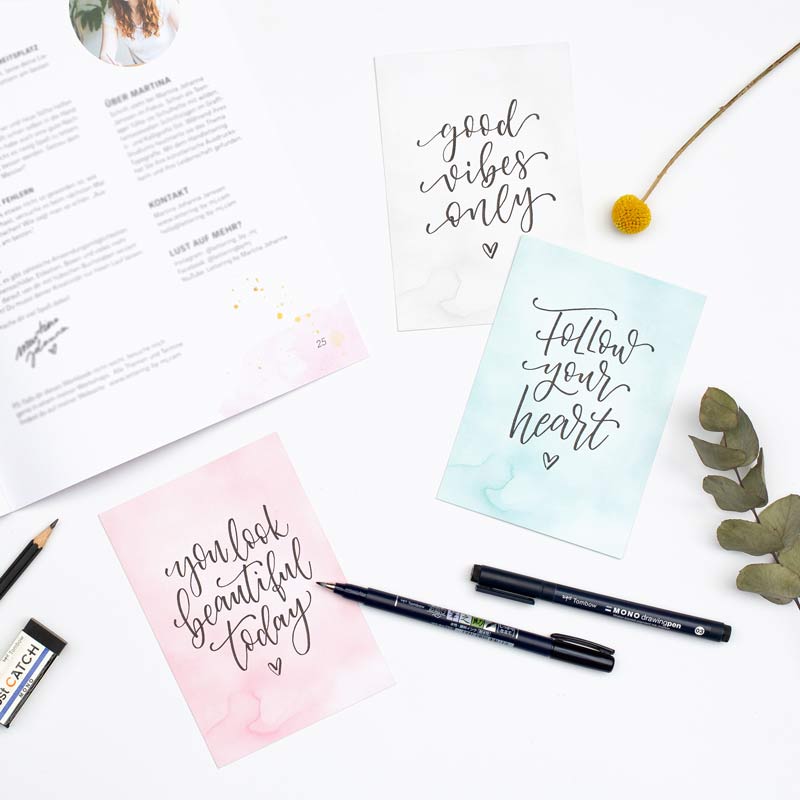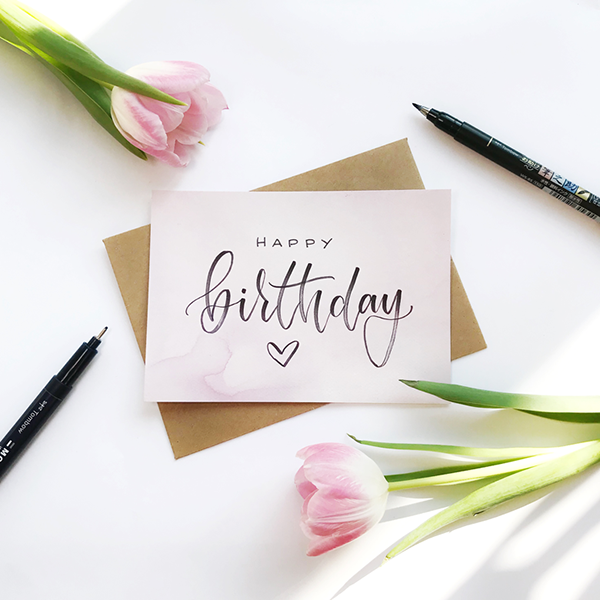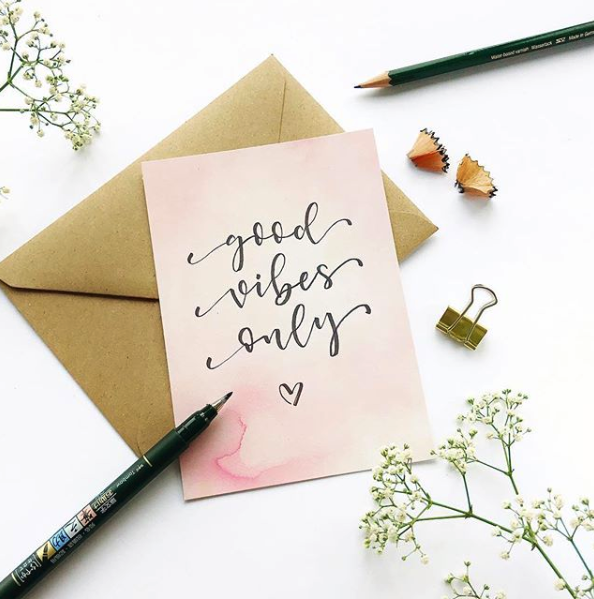
Brushlettering Modern Calligraphy – Die Motivation
In diesem Workshop geht es rund um die moderne Kalligrafie mit dem Brush Pen. Die moderne Kalligrafie ist besonders beliebt, wenn es um die Gestaltung von Hochzeits-Equipment wie Namensschildern, Einladungen oder Menükarten geht. Aber auch auf Briefumschlägen, Postkarten oder einfach nur so, der Stil der modernen Kalligrafie besticht durch ihre simple Schönheit.
Klassischerweise werden in der Kalligrafie Feder, Federhalter, Tinte und spezielles Papier benutzt, aber es gibt auch moderne Brush Pens, mit denen sich ganz unkompliziert ein sehr ähnliches Schriftbild zaubern lässt. Wie das funktioniert, worauf es ankommt und wie sich die Schriftzüge verzieren lassen, möchte ich euch in diesem Workshop zeigen.
Die Inhalte
Die feine Buchstaben von A bis Z
Wir üben das Alphabet von A bis Z in klein und groß mit dem feinen Brush Pen. Zusätzlich zeige ich dir eine feine Druckschrift, die den feinen Schriftzug im modernen Kalligrafie Stil schön und unaufdringlich begleitet.
Schnörkel
Schwünge und Schnörkel an den Buchstaben lassen deinen Schriftzügen aufleben. Ich zeige dir, wie und wo Schnörkel den Buchstaben den Feinschliff verpassen.
Schmuckelemente
Ich werde dir zeigen, wie du deine Schriftzüge ganz einfach mit schönen Blätter- und Blumenranken verzieren kannst.